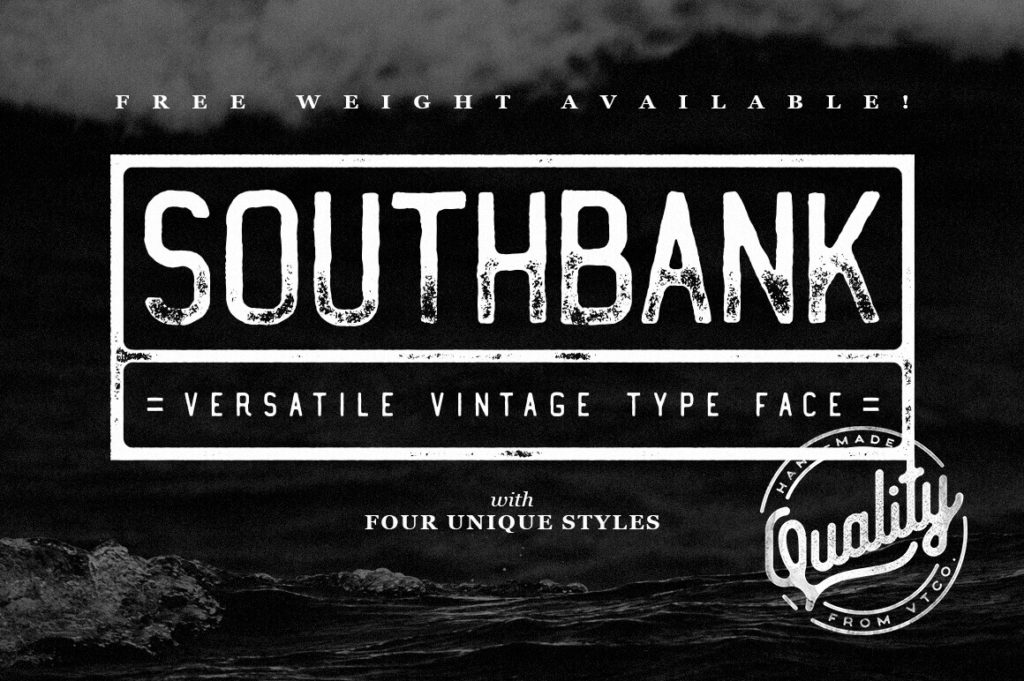
Шрифт Southbank
это выразительный акцидентный шрифт, разработанный канадским дизайнером Шоном Коуди (Sean Coady) для студии Vintage Type Company в 2016 году. Гарнитура стилизована под печатную машинку эпохи ретро-авангарда: брутальные засечки и характерный «печатный» рисунок букв создают атмосферу винтажной типографики. Шрифт Southbank кириллицу поддерживает на высоком уровне, сохраняя узнаваемый стиль оригинала. Он отлично подходит для создания афиш, заголовков в стиле лофт или гранж, а также для упаковки товаров с историческим колоритом. Скачать бесплатно можно по ссылке ниже.